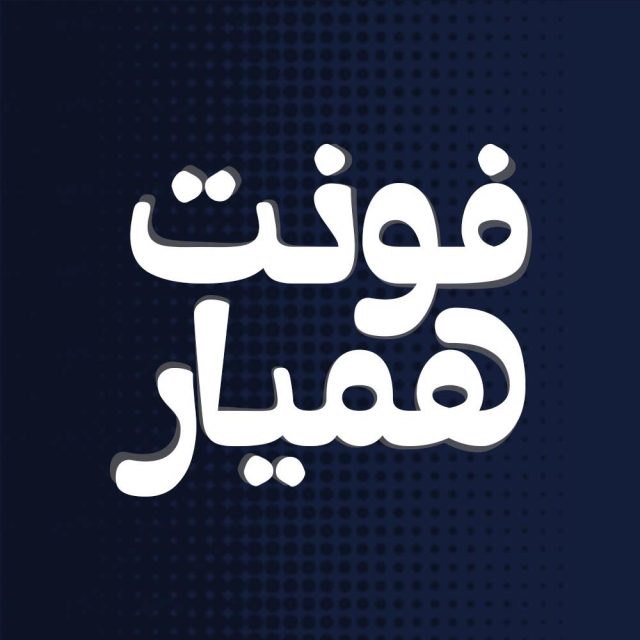
فونت فارسی همیار Hamyar Font
فونت همیار به لحاظ نرم افزاری ساختار ساده ای دارد و بیشتر مناسب استفاده در زمینه کارهای گرافیک ثابت است. مهارت و خلاقیت شما در تنظیم…
فونت همیار به لحاظ نرم افزاری ساختار ساده ای دارد و بیشتر مناسب استفاده در زمینه کارهای گرافیک ثابت است. مهارت و خلاقیت شما در تنظیم دستی چیدمان حروف و رنگ بندی مناسب می تواند در زیبایی بیشتر این فونت موثر باشد. از جمله ویژگی های مهم فونت همیار می توان به ضخامت بالای کلمات، برجستگی و جذابیت ظاهری اشاره کرد. در ادامه برای شما نمونه تایپ های این محصول حرفه ای رو آماده کردیم که میتونید مشاهده کنید.
پیشنمایش و نمونه تایپ های فونت همیار